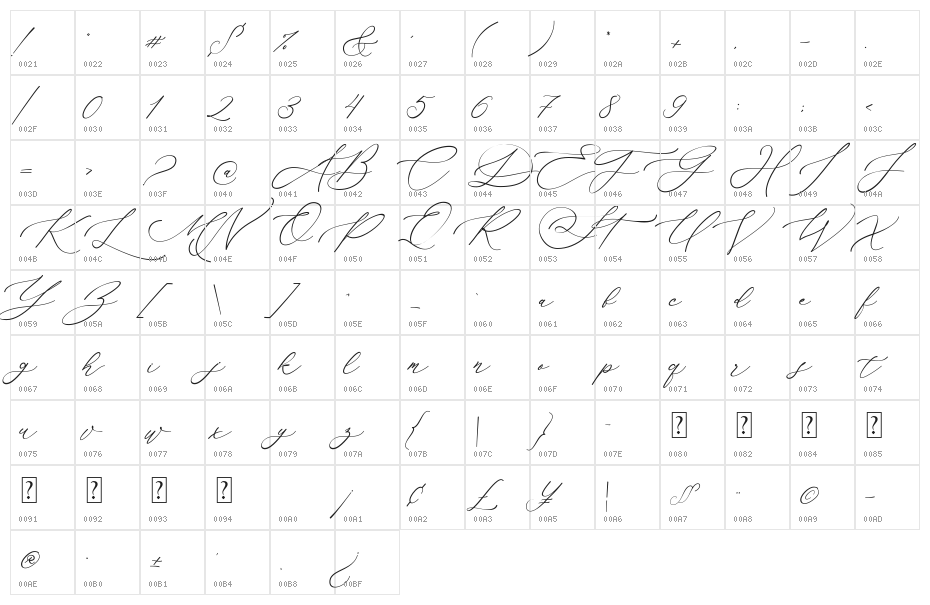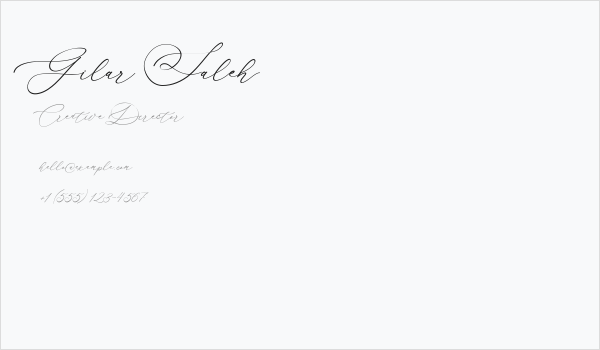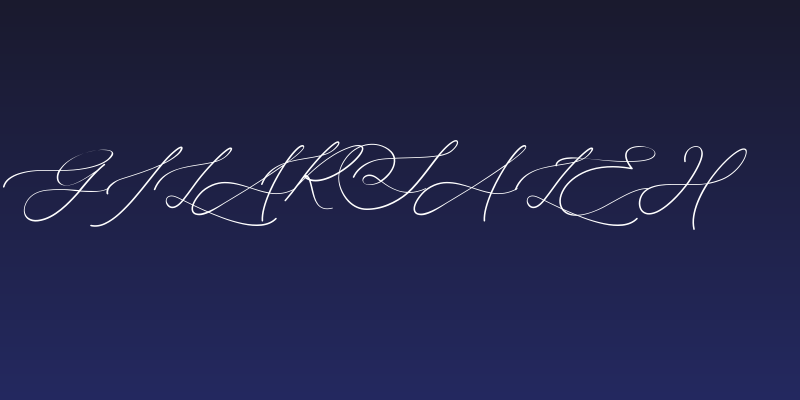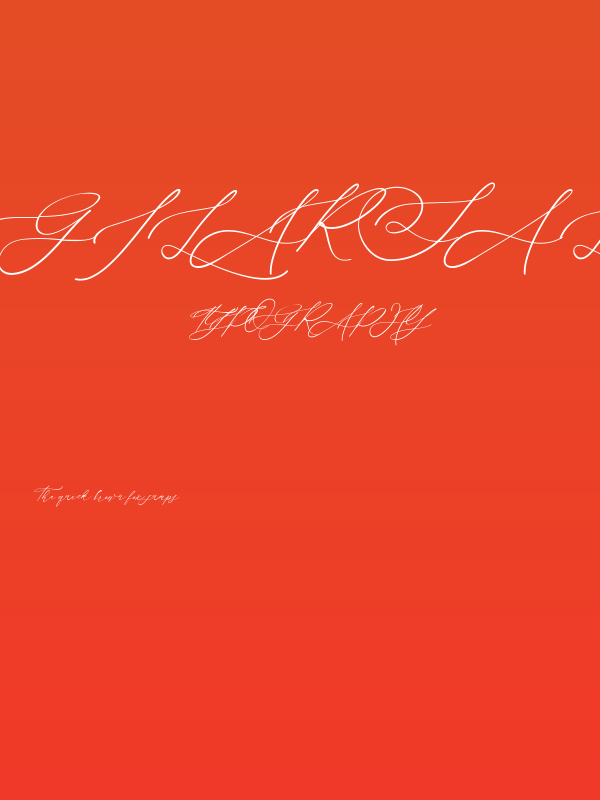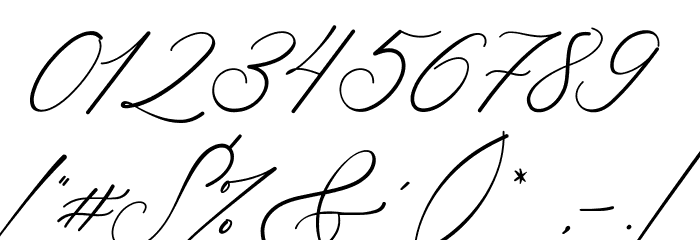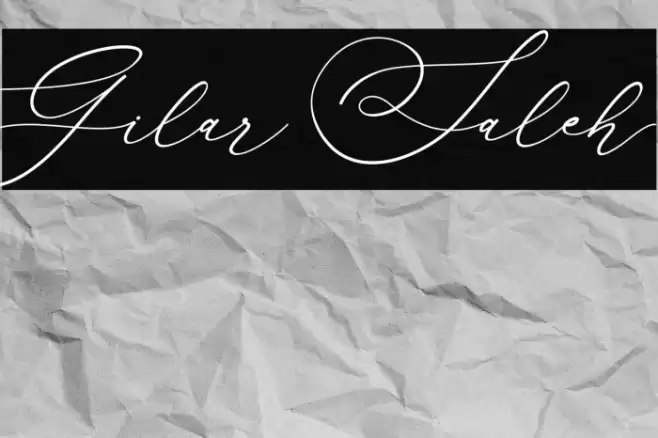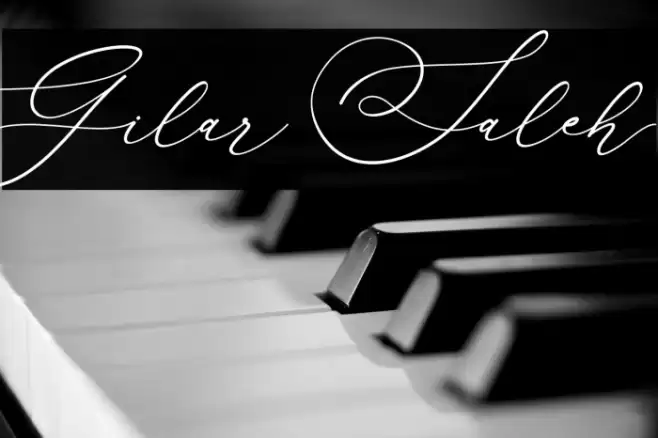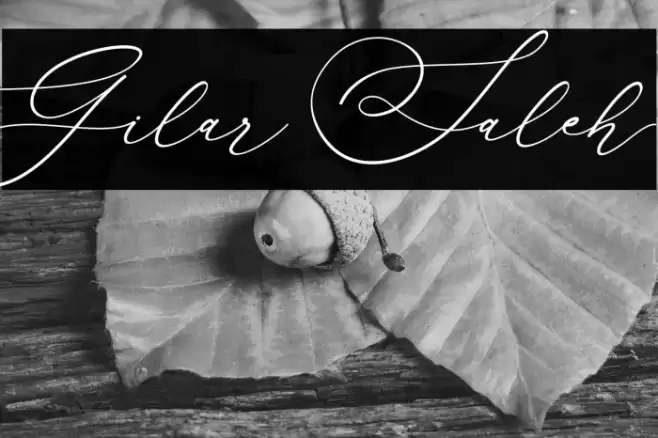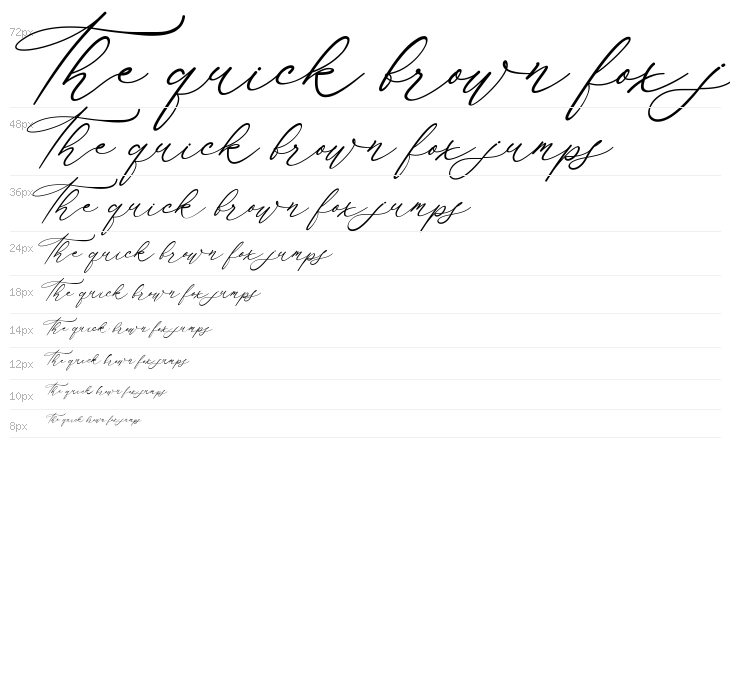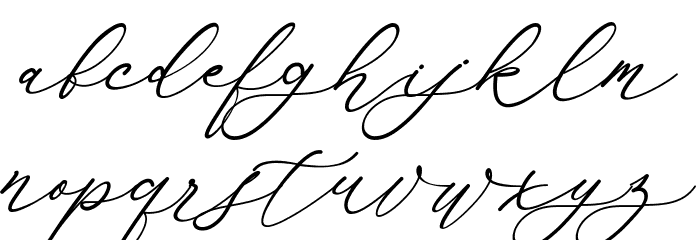
Gilar Saleh Font
| Stile generale | Elegant |
| Caso d'uso | Logos, Invitations, Decorative text |
| Progetti proposti | Ideal for wedding invitations, elegant branding, personal stationery, and artistic projects requiring a touch of class. |